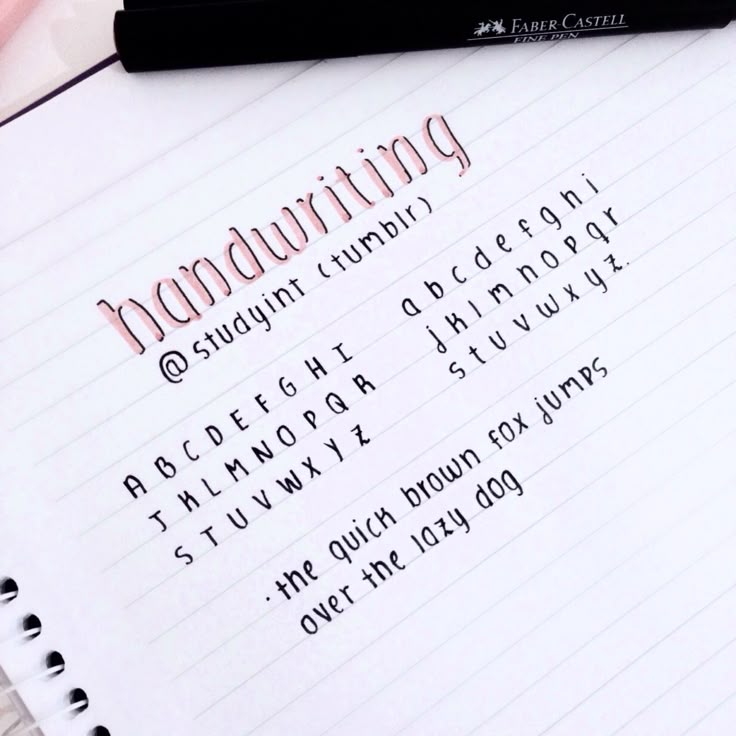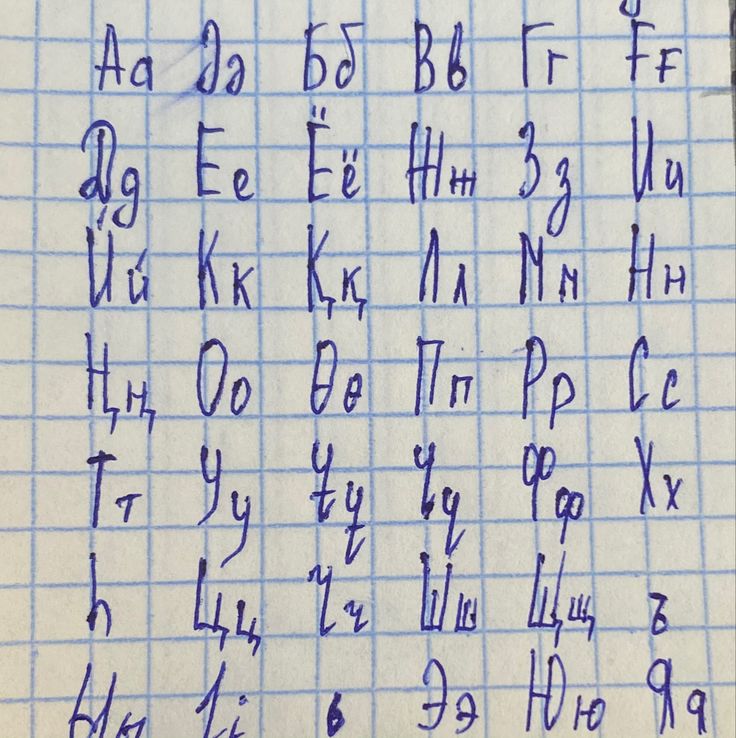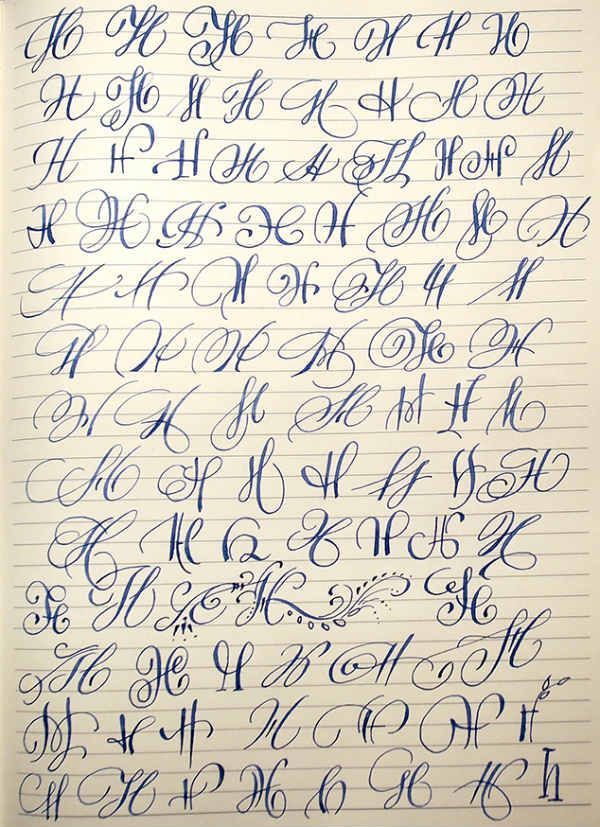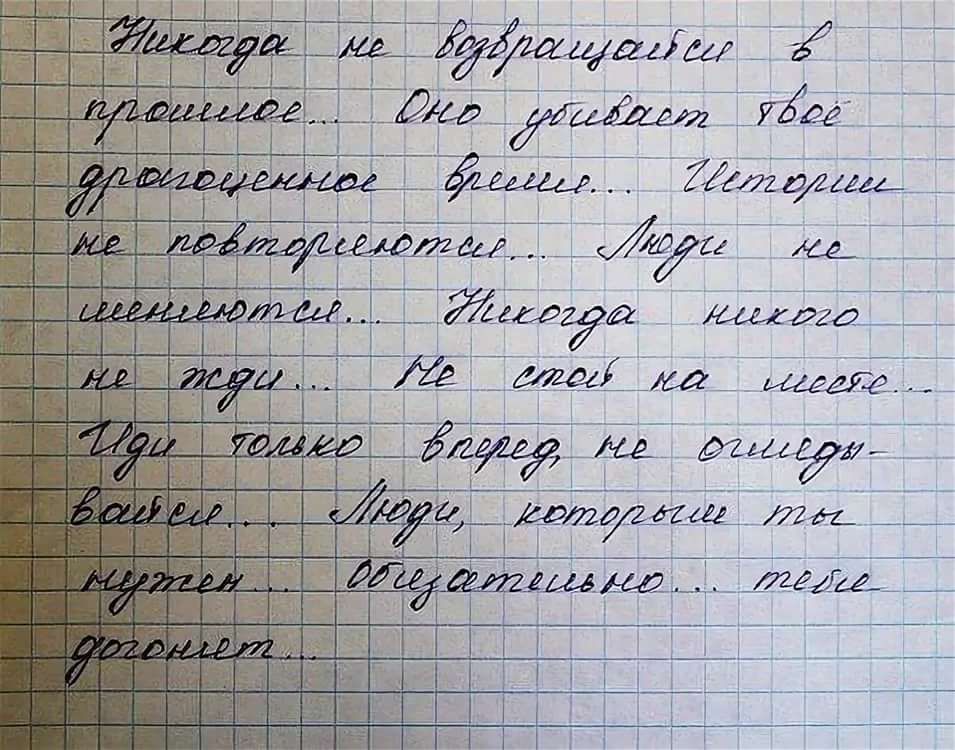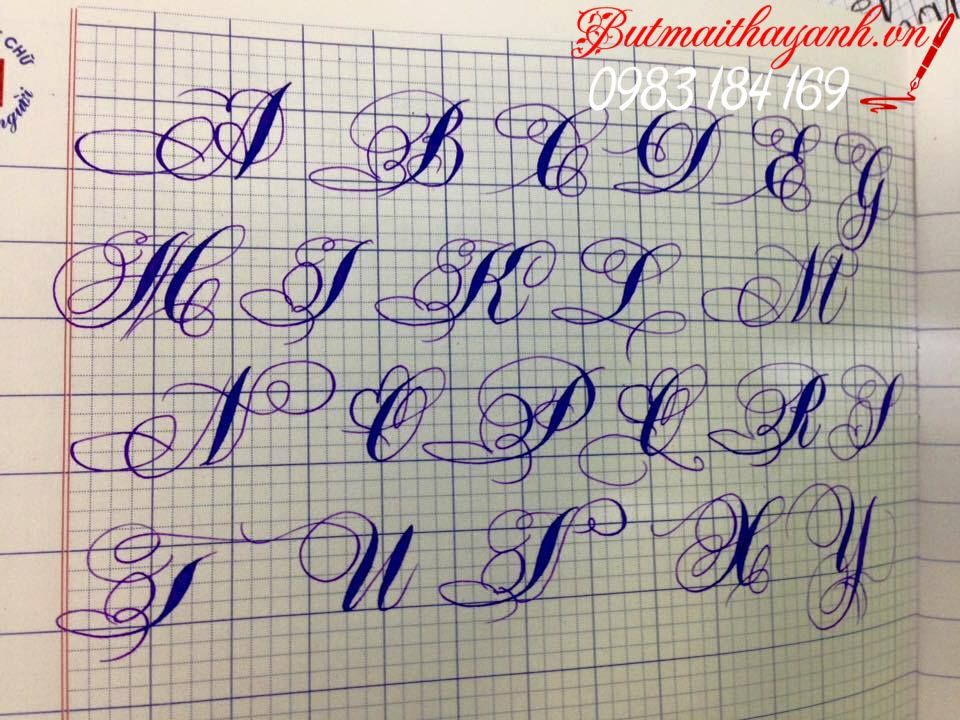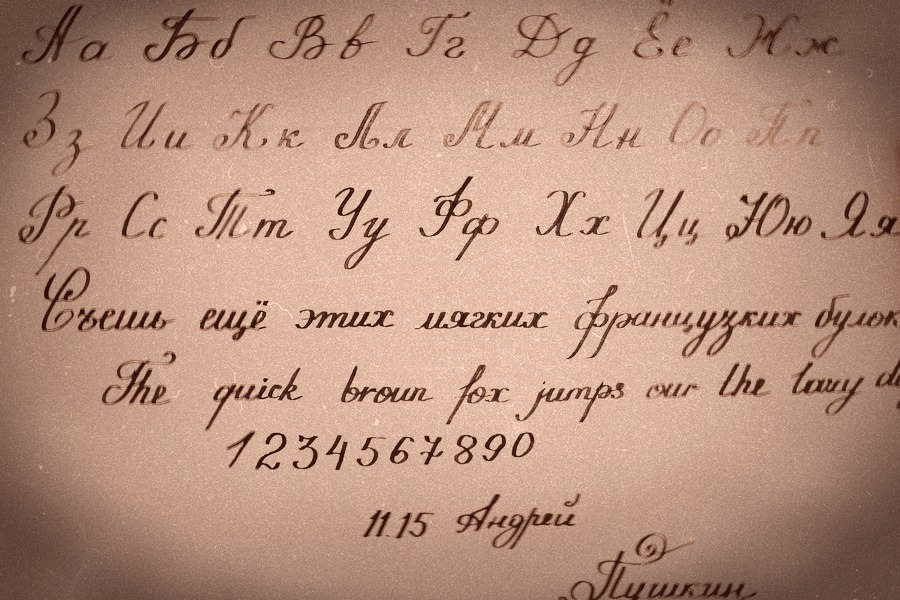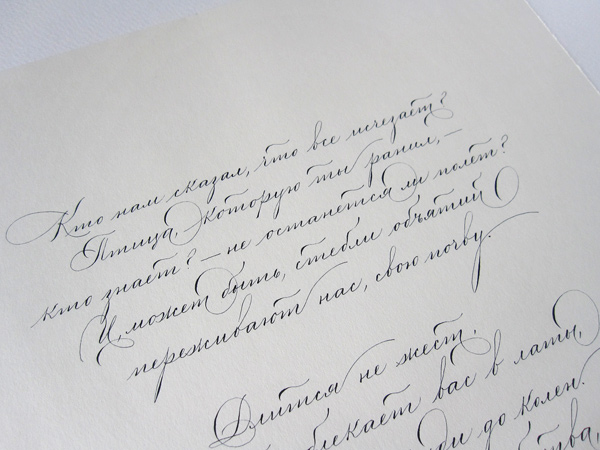
Красивый почерк научиться красиво писать алфавит. Как научиться писать красивым почерком: урок каллиграфии
Так уж повелось, что людям нравится всё красивое. Прекрасные люди, дома, творения — всё это вызывает неподдельное чувство восторга. Но не следует забывать и о приятных мелочах, например о нашем почерке. И здесь становится актуальным вопрос о том, как написать красиво букву, имя или даже письмо. Увы, просто захотеть здесь мало. Необходимо ещё существенно поработать над собой и техникой написания. Как это сделать, мы и поговорим в этой статье.
Общая информация
Казалось бы, мы с каждым годом всё меньше используем ручку, но вопрос о том, как написать красиво, не теряет свою актуальность.
Ровный, разборчивый и эстетически привлекательный почерк нужен по целому ряду причин:
- Исключает неправильное прочтение и последующие ошибки восприятия.
- Не вызывает у читающего раздражение.
- Дисциплинирует поток мыслей во время написания.
- Подходит для дарственных надписей и поздравительных открыток.
- Говорит в пользу человека и его характера.
- Обеспечивает красивую подпись.
Как видите, есть и явные, и косвенные преимущества. Кстати, как написать красиво, изучает целая наука — каллиграфия. Различные особенности почерка разбирает графология. Зная эти две науки, можно выработать стиль, который подсознательно будет вызывать у читающих симпатию и уважение к автору.
Чему стоит уделить внимание?
Всему. Наш почерк — это наш характер. Все завитки, закорючки, наклоны букв и нажим ручки рассказывают о нас каждому читателю. Поэтому просто взять и изменить стиль письма не получится. Так, красивый почерк более легко даётся спокойным и уравновешенным людям, что хорошо владеют кистью руки (то есть мелкой моторикой). Важным является и сознательное желание писать разборчиво, ровно и красиво. Навык письма зависит от наших волевых усилий и тренировок. Конечно, в первое время придётся концентрироваться на пределе. Но потом, со временем, правильное и образцовое написание будет даваться легче, пока вообще не станет привычкой.
Обучение
Итак, как написать красиво текст? Обучиться этому можно в любом возрасте. Необходимо применять только определённую технику. Как уже ранее упоминалось, этим занимается каллиграфия.
На данным момент существует полтора десятка направлений, которые достигли значительных высот. Некоторые алфавиты, используемые народами мира, являются настоящими шедеврами произведения. К таковым можно отнести персидскую вязь, китайскую каллиграфию и много других. Но нас интересует кириллица. Она обладает древней традицией и используется для обучения детей в начальных классах. Простая кирилличная каллиграфия знакома каждому — это прописи, которые школьники учатся писать в начальных классах. Но если школа была окончена давно, не волнуйтесь — время не утеряно. Ещё можно достичь высот в этом деле. Давайте разберёмся, как красиво написать слово.
Тренируем кисть руки
Начать нужно именно с этого. Ведь если не поставить кисть руки, то все другие попытки будут малорезультативными.
Для этого следует выполнять небольшую гимнастику, как то: круговые движения, растяжка, сжатие кулаков, сгибание/разгибание пальцев. Согласитесь, это несложно. После разминки (достаточно пяти минут) можно брать в руки ручку. Первоначально можно начать с фигур, таких как спирали и зигзаги. Затем следует писать в строчку без разрыва букву Ш, А и/или Г. Рядок одна, потом вторая, а затем и третья. При этом необходимо работать медленно, контролируя свои движения, прорисовывать буквы по контуру. Рисуя, следует концентрировать внимание на возникающих ощущениях в кисти и пальцах. Следует повторять буквы, пока не возникнет эффект автоматизма. После этого стоит попробовать писать быстрее. Следующий этап — уменьшение знака. Заниматься следует в тишине и спокойствии. Не следует забывать про хорошее освещение, плотную бумагу и беспроблемную ручку. Можно заниматься каждый день по 15-20 минут или через один, но уделяя уже по 30-40 мин.
Помогаем себе
Давайте поставим несложную, но приятную задачу.
Например — как красиво написать имя. Своё, само собой. Для этой цели можно использовать каллиграфический кирилличный алфавит.
Его можно приобрести в магазине канцтоваров или же, используя шаблон из мировой сети, создать самостоятельно. На этом этапе важная цель — это правильно и красиво выводить отдельные буквы — как строчные, так и прописные. Они должны идеально соответствовать образцам. Затем можно переходить на буквенные сочетания, которые соединяются линиями. А от этого до своего имени и рукой подать. Сначала можно использовать упрощенную форму. Например, писать не «Ольга» или «Александр», а «Оля» и «Саша». А потом уже из отдельных слов формировать предложения, а из них — полноценные тексты. Конечно, говорить об этом — не то же самое, что делать. Можно ли облегчить сей нелёгкий путь?
Есть ли здесь секрет успеха?
Кому-то каллиграфический почерк из-под собственных пальцев может показаться фантастикой. Как красиво написать письмо, не допустив при этой ужасных букв?
Что ж, специально для тех, кто задаётся этим вопросом, следует приоткрыть важный секрет — нужна частая практика.
Да, писать рукой придётся значительно больше, нежели обычно. Переписывая определённый текст или составляя собственный, следует не спешить. Хотя зависать на каждой отдельной букве тоже не следует. Необходимо следить за нюансами:
- Буквы должны иметь одинаковый размер.
- Соблюдайте наклон.
- Писать следует равномерно. Это относится как к буквам, так и к словам.
- На первое время можно использовать косую линейку. В последующем обязательно следует перейти на нелинованную бумагу.
- Следует проследить, чтобы края букв не вырывались вверх или не сползали вниз.
- Смотрите: между словами должны быть пробелы одинакового размера.
- Уделяйте внимание и знакам препинания. Они должны быть одинаковыми, чёткими, разборчивыми.
Когда я смотрю на фрагмент русского почерка, я обычно могу сделать предположение о поле автора, его возрасте, уровне образования, а иногда и характере. Так что было бы жаль потерять этот дополнительный источник информации о людях, с которыми вы имеете дело.
Нужно иметь представление: что и как уже написано, как сейчас пишут, как не пишут. В любом деле важнее всего система координат, в которой ты существуешь. Для пишущего человека такой системой должны быть все тексты, которые ему доступны